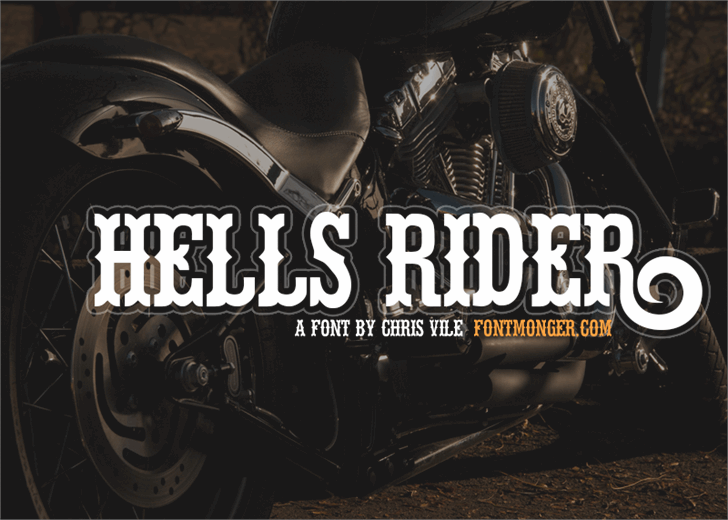
Hells Rider Font – Download Grátis
A fonte “Hells Rider” é uma escolha perfeita para qualquer projeto que requer estilo agressivo e robusto. Desenvolvida pelo designer Hamilton, esta elegante família de gótico inclui três estilos fundamentais: solido, itálico e quebrado, oferecendo um nível incomparável de personalização. Se você busca uma fonte que se destaca tanto no ambiente digital quanto na impressão, a “Hells Rider” é sua melhor escolha. Para uso empresarial ou comercial sem necessariamente licenças prévias, é crucial mencionar as restrições. Acredita-se que estejam disponíveis números de licenciamento em uma versão licenciada completa. Portanto, certifique-se de ter todas as autorizações necessárias antes de começar a usar esta fonte em qualquer projeto com fins lucrativos. Com sua gama de estilos sólidos e erodidos, “Hells Rider” oferece um grau incomparável de personalização para tornar suas ideias únicas e memoráveis. É uma escolha ideal para aplicativos gráficos como logotipos, materiais de marketing ou design editorial, garantindo que seu trabalho brilhe na web e na impressão. A fonte é perfeitamente adaptada a diferentes tamanhos de texto, tornando-a um recurso valioso em qualquer projeto de design.